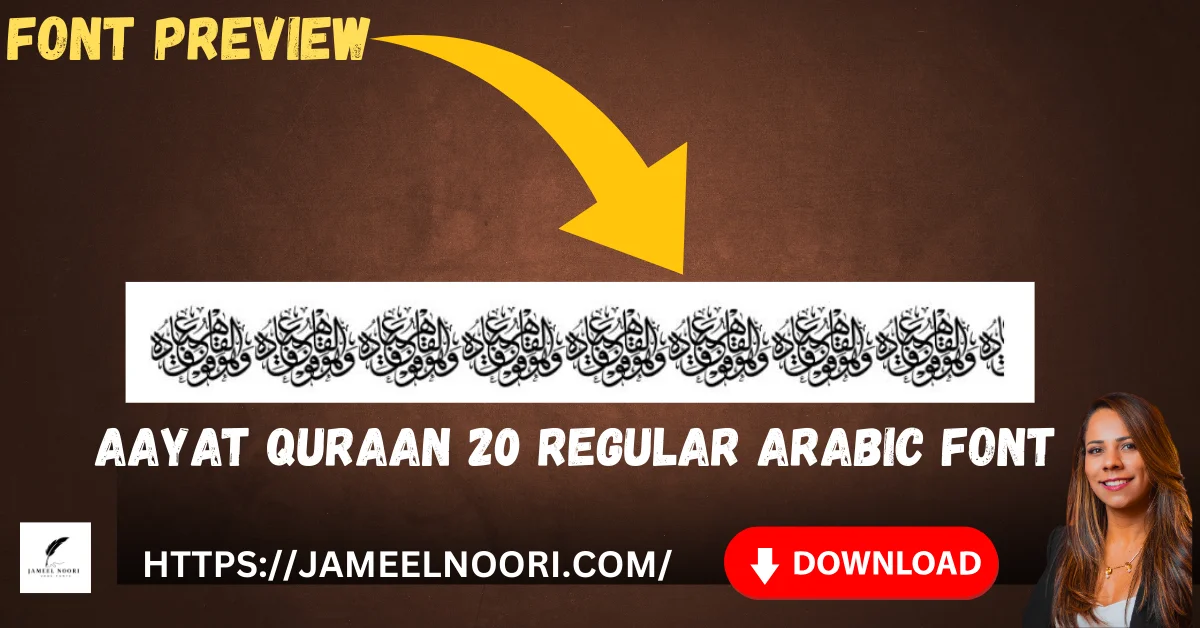
Aayat Quraan 20 Regular Arabic Font – Guide for Quranic Calligraphy
Introduction to Aayat Quraan 20 Regular Arabic Font
Aayat Quraan 20 Regular Arabic Font ek Regular TrueType Font hai jo specially Quranic text aur Arabic calligraphy ke liye design kiya gaya hai. Ye font Pakistan me designers aur Urdu font lovers ke liye kaafi popular hai.
What Are The Features of Aayat Quraan 20 Regular Arabic Font?
Ye font feature-rich aur user-friendly hai. Iske main features me shamil hain:
Use CasesQuranic text, posters, digital art, educational content
Why Choose Aayat Quraan 20 Regular Arabic Font?
Aayat Quraan 20 Regular Arabic Font ko choose karne ki wajah ye hai ke ye readability aur elegance dono provide karta hai. Pakistan me Urdu aur Arabic fonts designers ke liye ye expert choice hai.
• Easy-to-read calligraphy style – clear and beautiful
• Perfect for Islamic books, posters, aur digital use – versatile
Where Can You Use Aayat Quraan 20 Regular Arabic Font?
Aayat Quraan 20 Regular Arabic Font versatile hai aur kai projects me use ho sakta hai. Yeh perfect hai:
• Quranic texts aur religious publications – authentic look
• Educational materials aur e-books – clear readability
• Posters, banners, aur calligraphy art – professional design
• Social media graphics aur digital designs – attractive posts
• YouTube thumbnails – attention-grabbing titles
• Madaris worksheets – educational material
What Makes Aayat Quraan 20 Regular Font the Best Arabic Font in Pakistan?
Ye font Pakistan me designers aur calligraphy enthusiasts ke liye best arabic font ban chuka hai. Iske reasons:
• Elegant calligraphy aur readable structure – beautiful design
Aayat Quraan 20 Regular Arabic Font preview for Urdu and Arabic projects
Preview of Aayat Quraan 20 Regular Arabic Font showing its readability and compatibility for multiple digital projects.